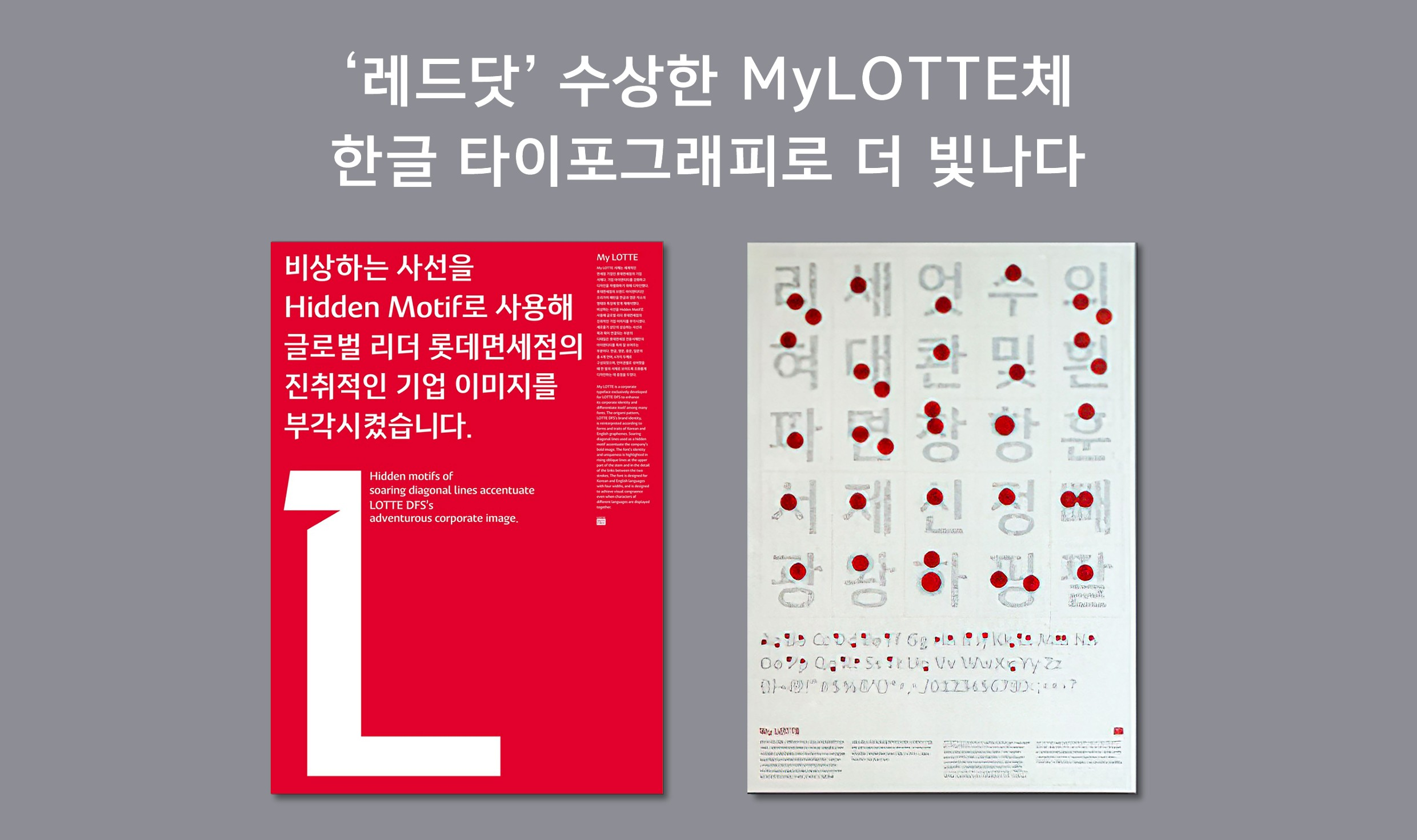
독일 레드닷 '커뮤니케이션 부문, 타이포그래피 분야'의 '베스트 오브 더 베스트'를 수상한 '마이롯데'체
1989년 설립된 ㈜윤디자인그룹(대표 편석훈)은 국내 최초로 디지털 한글 글꼴을 개발한 이래, 800여 종에 달하는 디지털 글꼴을 선보여 왔다.
특히 본문용 한글 글꼴의 베스트셀러라 할 수 있는 ‘윤고딕’과 ‘윤명조’의 경우, 20년 이상 꾸준한 업그레이드와 새로운 시리즈 개발로 출판인쇄 분야와 시각디자인 영역 전반에서 ‘윤서체’라는 고유명사를 탄생시키기도 했다.
또한 현대자동차의 ‘모던 H’체, 신한카드의 ‘신한세빛’체, 롯데면세점의 ‘마이롯데(MyLotte)’체 등 국내 대기업들의 전용서체부터, 대신증권·신한카드·하나금융그룹·IBK기업은행 등 금융기관, 고양시·서울시·전라남도·포천시 등 지자체 서체까지 개발하며 서체를 활용한 브랜드 가치 제고에 기여해왔다.
글꼴 디자인을 브랜드의 관점으로 바라보는 윤디자인그룹만의 경쟁력은 여러 수상 실적을 통해서도 입증됐다. 올 초와 연말 각각 수상한 ‘대한민국 고객만족·브랜드 경영대상’(브랜드디자인 부문)과 ‘대한민국 문화경영대상’(글자체 브랜드 부문)을 비롯하여, 2014년 대한민국디자인대상 및 산업통상자원부장관상, 2011년 문화체육관광부장관 표창 등 다방면에서 기업 가치를 인정받았다.
올해 개발한 기업 전용서체인 ‘마이롯데’체의 경우, 지난 8월 세계 3대 디자인 어워드 가운데 하나인 독일 레드닷(Red Dot Design Award)에서 ‘커뮤니케이션 부문, 타이포그래피 분야’의 ‘베스트 오브 더 베스트’를 수상하는 쾌거를 올리기도 했다. 올 초 ㈜윤디자인그룹 편석훈 대표는 ‘글꼴 디자인과 브랜드, 콘텐츠의 관계를 탐구하고 창조하는 디자인 전문가 집단’으로서의 미래 비전을 선포하고, 글꼴 디자인·브랜딩·콘텐츠 3개 핵심 사업부서의 조직 정밀화, 연구 인력 및 투자 규모 확충 등을 통해 내실을 다지고 외연을 확장해간다는 경영 방침을 구현해 가고 있다.
2019년 창립 30주년을 맞는 ㈜윤디자인그룹은 내년 한 해 동안 브랜드 리뉴얼과 더불어, 자사 신서체 적극 개발, 글꼴 디자인과 타이포그래피를 중심으로 한 신사업 개척 등에 공격적으로 나설 계획이다. 편석훈 대표는 “단순히 글꼴만을 디자인하는 기업이 아닌, 글꼴 디자인을 바탕으로 매력적인 브랜딩과 양질의 콘텐츠 생산까지 가능한 디자인 전문가 집단으로서 세계 시장을 개척해나갈 것”이라는 계획을 밝혔다.
[2017 대한민국 문화경영대상 ㈜윤디자인그룹] 디지털 글꼴 800종 개발…전용서체 ‘일인자’
1989년 설립된 ㈜윤디자인그룹(대표 편석훈)은 국내 최초로 디지털 한글 글꼴을 개발한 이래, 800여 종에 달하는 디지털 글꼴을 선보여 왔다.
특히 본문용 한글 글꼴의 베스트셀러라 할 수 있는 ‘윤고딕’과 ‘윤명조’의 경우, 20년 이상 꾸준한 업그레이드와 새로운 시리즈 개발로 출판인쇄 분야와 시각디자인 영역 전반에서 ‘윤서체’라는 고유명사를 탄생시키기도 했다.
또한 현대자동차의 ‘모던 H’체, 신한카드의 ‘신한세빛’체, 롯데면세점의 ‘마이롯데(MyLotte)’체 등 국내 대기업들의 전용서체부터, 대신증권·신한카드·하나금융그룹·IBK기업은행 등 금융기관, 고양시·서울시·전라남도·포천시 등 지자체 서체까지 개발하며 서체를 활용한 브랜드 가치 제고에 기여해왔다.
글꼴 디자인을 브랜드의 관점으로 바라보는 윤디자인그룹만의 경쟁력은 여러 수상 실적을 통해서도 입증됐다. 올 초와 연말 각각 수상한 ‘대한민국 고객만족·브랜드 경영대상’(브랜드디자인 부문)과 ‘대한민국 문화경영대상’(글자체 브랜드 부문)을 비롯하여, 2014년 대한민국디자인대상 및 산업통상자원부장관상, 2011년 문화체육관광부장관 표창 등 다방면에서 기업 가치를 인정받았다.
올해 개발한 기업 전용서체인 ‘마이롯데’체의 경우, 지난 8월 세계 3대 디자인 어워드 가운데 하나인 독일 레드닷(Red Dot Design Award)에서 ‘커뮤니케이션 부문, 타이포그래피 분야’의 ‘베스트 오브 더 베스트’를 수상하는 쾌거를 올리기도 했다. 올 초 ㈜윤디자인그룹 편석훈 대표는 ‘글꼴 디자인과 브랜드, 콘텐츠의 관계를 탐구하고 창조하는 디자인 전문가 집단’으로서의 미래 비전을 선포하고, 글꼴 디자인·브랜딩·콘텐츠 3개 핵심 사업부서의 조직 정밀화, 연구 인력 및 투자 규모 확충 등을 통해 내실을 다지고 외연을 확장해간다는 경영 방침을 구현해 가고 있다.
2019년 창립 30주년을 맞는 ㈜윤디자인그룹은 내년 한 해 동안 브랜드 리뉴얼과 더불어, 자사 신서체 적극 개발, 글꼴 디자인과 타이포그래피를 중심으로 한 신사업 개척 등에 공격적으로 나설 계획이다. 편석훈 대표는 “단순히 글꼴만을 디자인하는 기업이 아닌, 글꼴 디자인을 바탕으로 매력적인 브랜딩과 양질의 콘텐츠 생산까지 가능한 디자인 전문가 집단으로서 세계 시장을 개척해나갈 것”이라는 계획을 밝혔다.